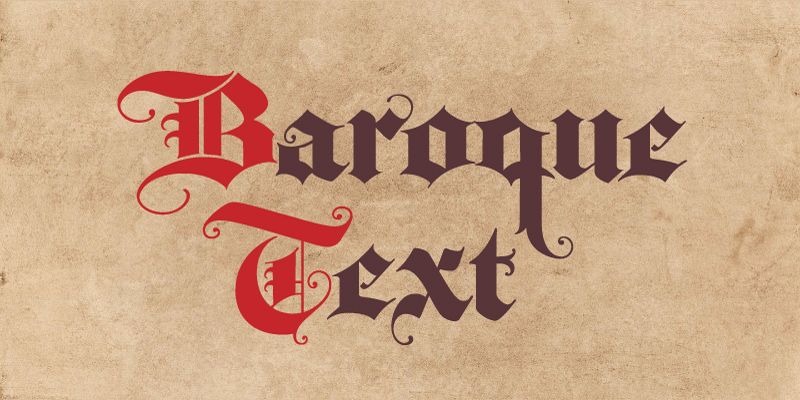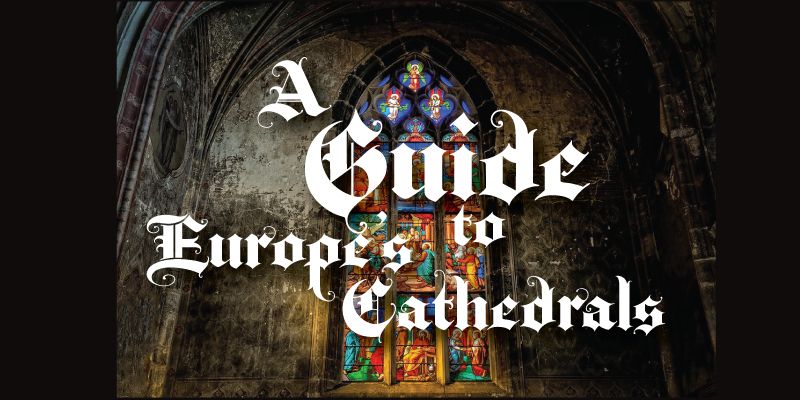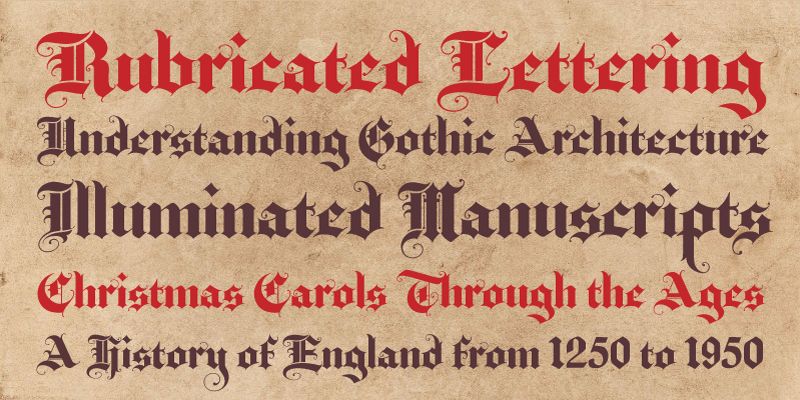
Baroque Text ist eine Schrift im Blackletter-Stil mit extravaganten Schnörkeln und Formen. Inspiriert von der Handschrift in einem alten Kalligrafiebuch ist diese Schrift gleichermaßen schön und eindrucksvoll.